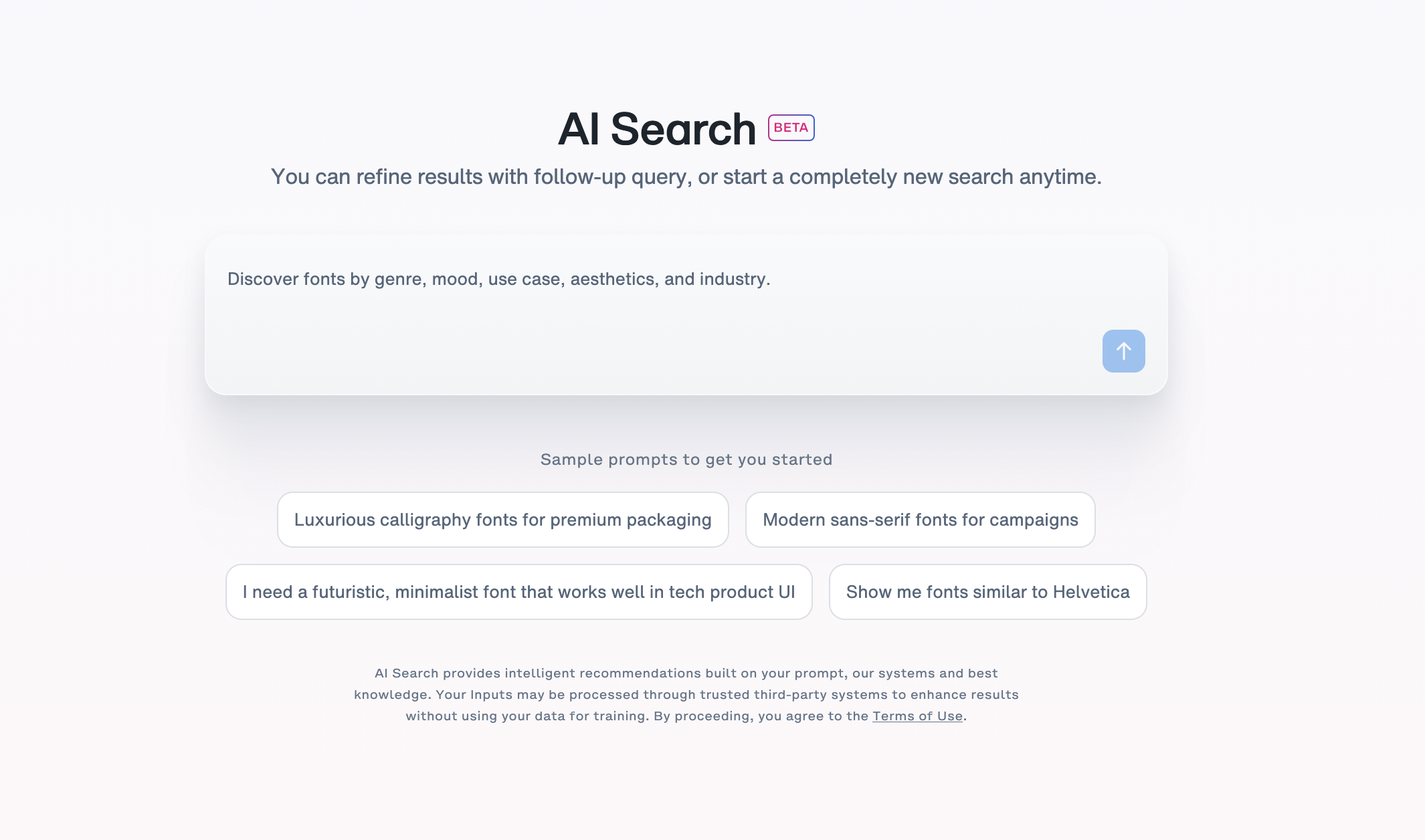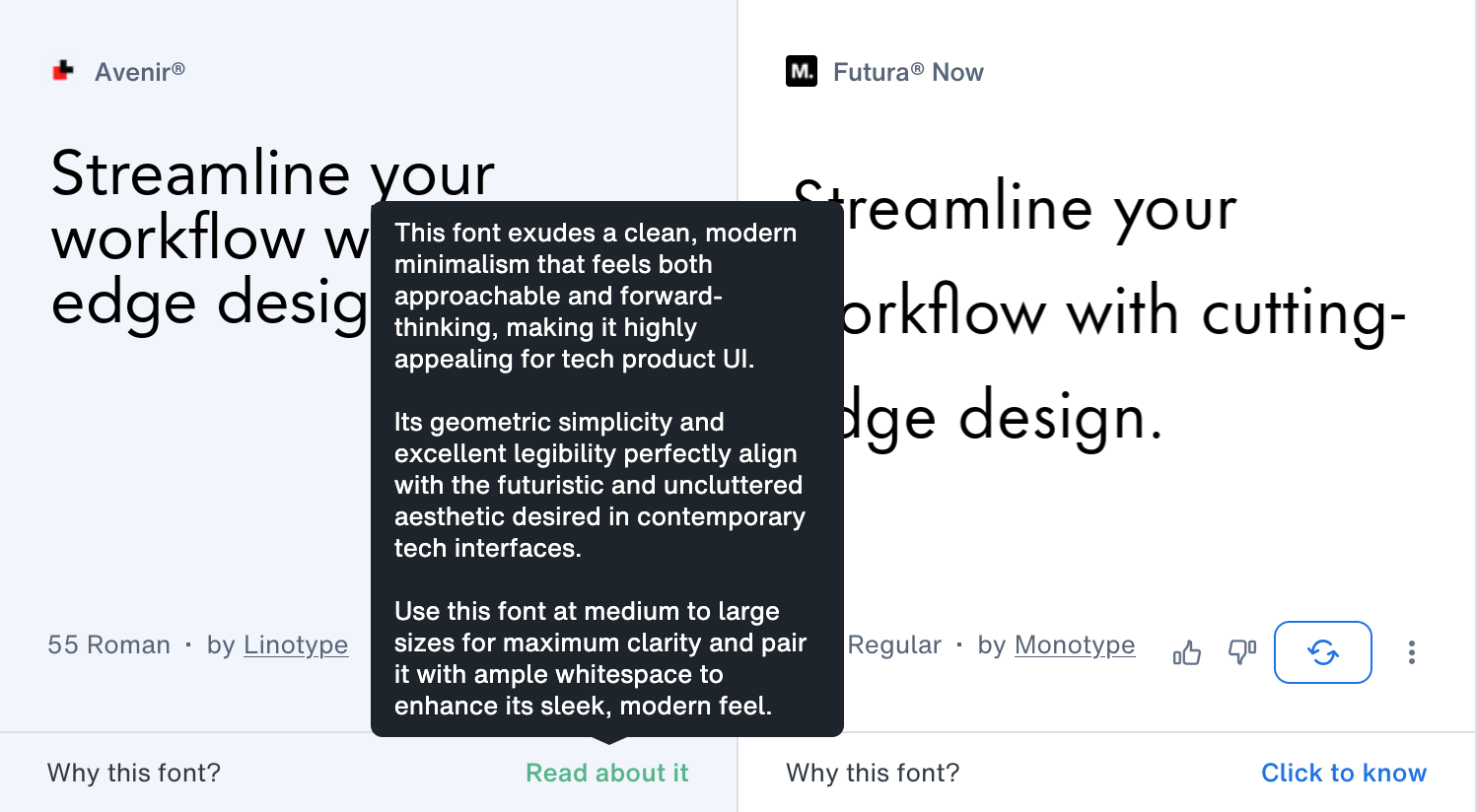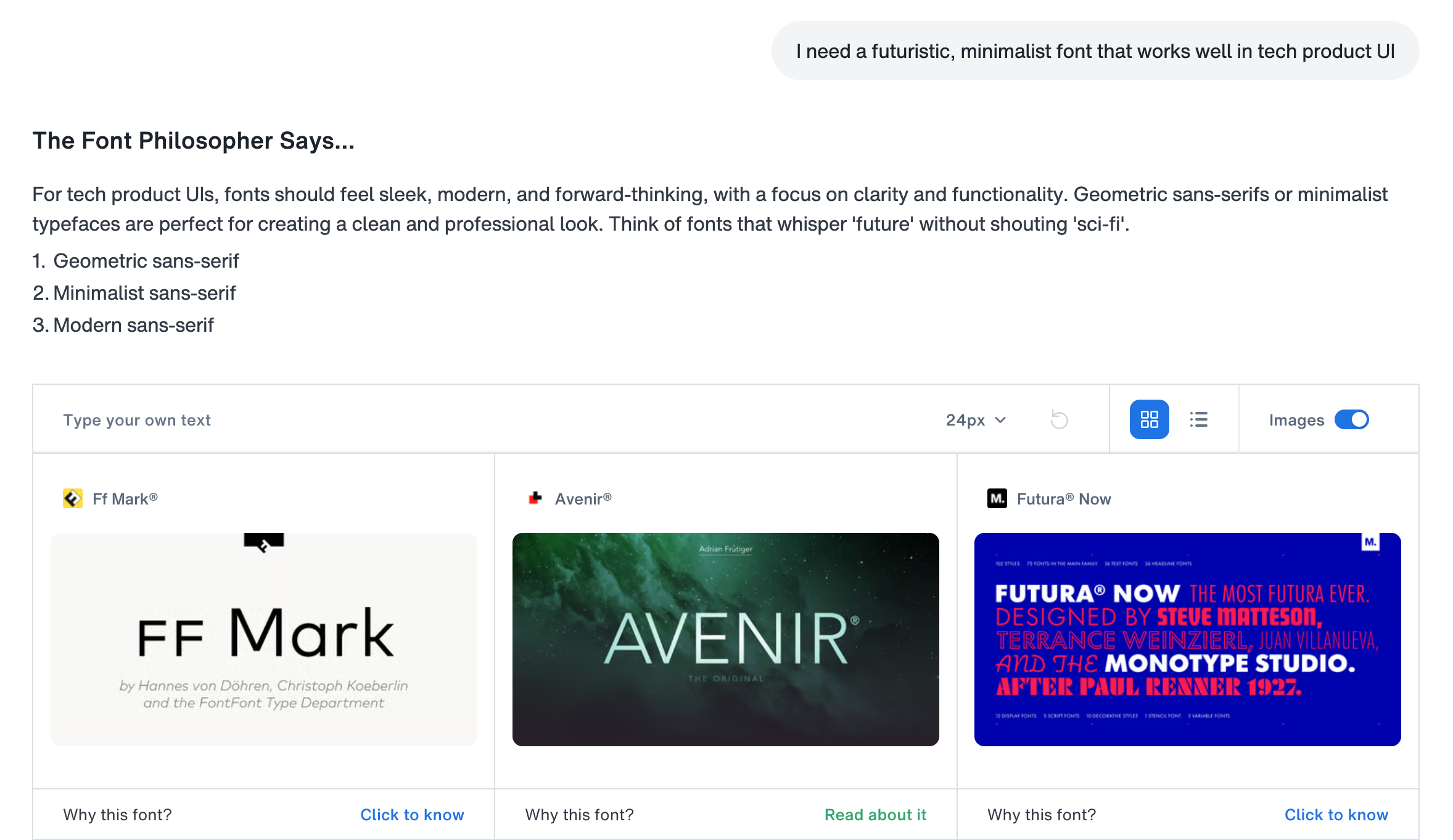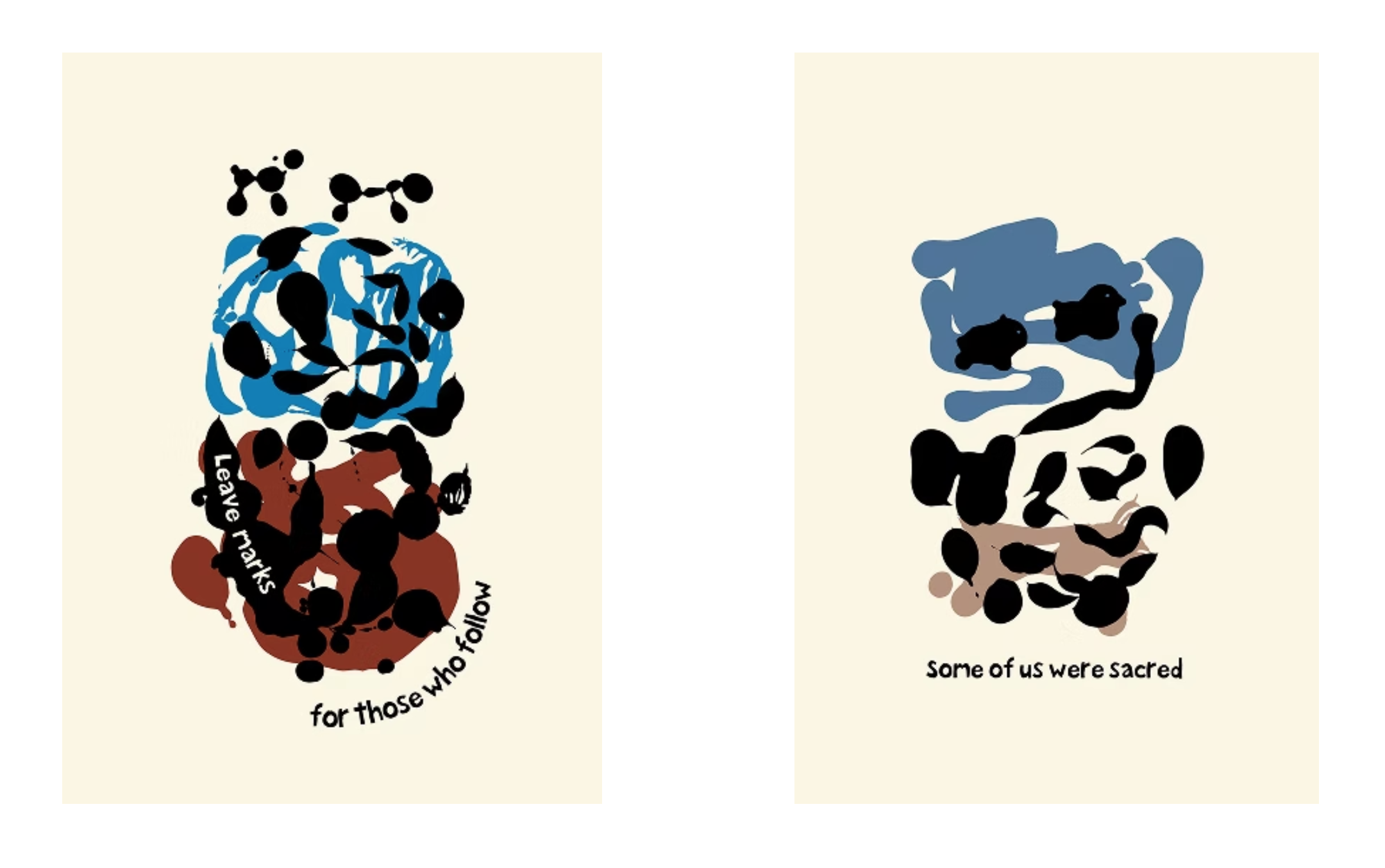
蒙纳字库(Monotype)推出字体 AI 检索工具,带来全新检索与探索体验
近日, 蒙纳(Monotype)正式发布全新字体检索与探索工具 AI Search。这款创新工具从根本上改变设计师、品牌方及创意团队寻找排版灵感、为各类项目匹配适配字体的方式。
目前,该工具已在 Monotype Fonts(国际版)上线,支持英语、法语、德语、西班牙语与葡萄牙语多语种操作。
告别繁琐筛选,开启对话式创意探索
蒙纳携手 4500 余家字体合作方,打造了超 25 万款字体的全球资源库。而 AI Search 的研发初衷,正是为了提升这一庞大字库的检索效率。工具深度融合蒙纳的检索智能技术与专业字体造诣,助力创作者精准找到所需字体,更为融合各类创意应用、设计工具、平台及新一代数字化工作流提供了无限可能。
传统字体检索依赖有限的筛选条件、标签分类,创作者往往需要反复翻找,而蒙纳 AI Search 以自然语言指令彻底替代了这一模式,让超 25 万款字体触手可及。创作者只需用语言描述设计氛围、品牌特质、字体风格或实际应用场景,就能以对话的方式找到理想字体。工具将自然的对话指令转化为精心筛选、贴合场景的字体推荐,让寻找适配字体的过程变得如同描述创作构想一般直观自然。
蒙纳首席字体官 Mike Matteo表示:“寻找合适的字体,不该如同大海捞针。AI Search 让创意工作流迎来全新升级。在传统检索模式中,设计师不得不让自己的创作构想迁就有限的筛选条件、分类目录与体系。而 AI Search 打造了更智能的检索系统,它能读懂创作者的思维与表达,捕捉那些藏在情绪、氛围与创作初衷里的需求。这是一种更高效、更贴合人本的方式,让创意构想能够顺畅转化为排版表达,最终落地为实际的创意作品。”
该工具将全面整合于 Monotype Fonts 平台,从这一全球最受信赖的字体生态中,为用户提供高效、精准且贴合字库状态的检索结果。
创意探索的全新范式
选配合适的字体,是创意工作流中至关重要的一环。优化这一环节,能帮助企业重新赢回高达 35% 的创意时间。蒙纳相关调研显示,62% 的受访企业表示,引入人工智能与自动化技术后,工作效率与创意产出实现双重提升。此外,82% 的创作者将排版设计列为创意决策的三大核心要素之一,85% 的创作者认为,选择独具辨识度的字体,是塑造品牌个性的关键之举。
AI Search 大幅减少创意工作流的中断,化身创作者身边的虚拟字体顾问,将创意需求转化为可落地、贴合场景的字体推荐,核心优势体现在:
• 从蒙纳全球字库中,为用户精心筛选个性化字体推荐
• 支持字体即时预览,助力创作者快速评估适配性
• 为字体适配性提供语义化解读,阐释排版设计逻辑
• 检索结果贴合实际字体库存,确保推荐字体可用
蒙纳执行创意总监 Terrance Weinzierl 表示:“AI Search 是强大的创意解读器,让字体检索与探索体验迈入全新时代,打破标签、品类与专业术语的限制。创作者能够跟随设计直觉与构想的节奏,以氛围、情绪为关键词进行检索,这不仅缩短检索时间,更能让整个过程更具价值。这是一款懂创作者语言的检索工具,能将模糊的创意想法,转化为精准的字体选择。”
艺术家实践案例:从创作构想到排版表达的完美落地
蒙纳 AI Search 已在实际创作中得到应用,助力创作者将抽象的创意构想,转化为细腻、贴合需求的排版决策。
艺术家 Max Trutt 在 Il Gattopardo 艺术中心完成驻留创作后,启动了全新的“艺术家之书”创作项目,该作品融合文字与丙烯插画艺术。他摒弃传统的字体筛选方式,借助 AI Search 的自然语言指令功能,不断迭代自己的创作构想。这一过程让他能够大胆尝试、探索不同的设计方向与视觉基调,最终为插画部分选定 FF Bokka™字体。这款字体兼具灵动趣味与历史底蕴,实现了与画面的完美融合;而书籍的纯文字页面,则选用了更简洁素雅的 Brother 1816 字体。
Trutt 评价道:“蒙纳 AI Search 让我无需纠结技术参数,只需描述创作参考与设计期待,就能畅游浩瀚的字体世界。它将我的艺术直觉,转化为兼具灵动趣味与历史厚重感的排版表达,让作品拥有了独属于自己的字体语言。”
此次创作最终诞生 14 件艺术作品,将插画与 AI Search 精心筛选的排版设计融为一体。该作品将以限量版艺术家之书《Look, No Humans (Animal’s March)》的形式正式发布,数字创作与排版设计环节由 Trutt 与 Peter Trudolubovs 联合完成。
重新定义字体检索
蒙纳 AI Search 以高效、精准、赋能创意为核心设计理念,为每一个字体推荐提供语义化解读,将创意需求转化为定制化的字体推荐清单。它让创作者更快找到适配字体,更以全新的检索逻辑挖掘更多字体可能,为创意探索与灵感迸发注入全新活力。
核心优势:
• 高效提效:大幅缩短字体探索时间,减少创意工作流中断,让团队快速进入设计环节
• 精准贴合:输出贴合场景、适配需求的检索结果,减少试错成本
• 清晰笃定:为字体推荐提供语义化的适配解读,支持即时预览,让团队理解字体适配逻辑,做出更笃定的创意决策
• 激发创意:创作者可通过自然语言描述氛围、品牌个性或表达风格探索字体,还能以自然的对话式追问优化检索,解锁更多灵感可能
蒙纳的全球体库满足世界各地的排版设计需求,AI Search 将人工智能技术与蒙纳的专业字体库、权威设计积淀深度融合,让字体检索与探索从传统的筛选模式,升级为更贴合人本的对话式工具,助力打造更高效的工作流、更优质的创意作品,让创意决策更可靠。